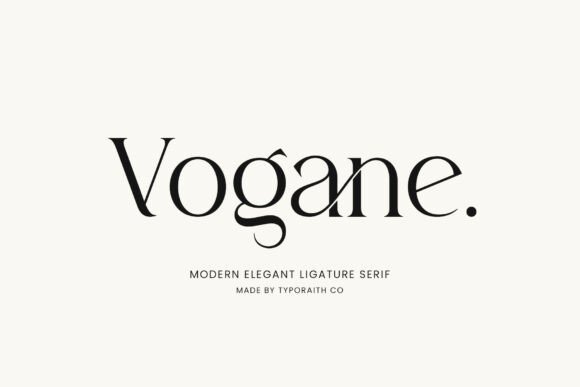
Vogane
適切なデザイン要素を見つけるのは難しい場合がありますが、Voganeは作品を即座に引き立てる優れたコレクションを提供します。
精密に作られたVoganeは、クリーンなベクター、滑らかなタイポグラフィ、そして安心のための商用ライセンスを提供します。
POD(オンデマンド印刷)製品、結婚式の招待状、またはソーシャルメディアのグラフィックを作成している場合でも、Voganeは理想的です。